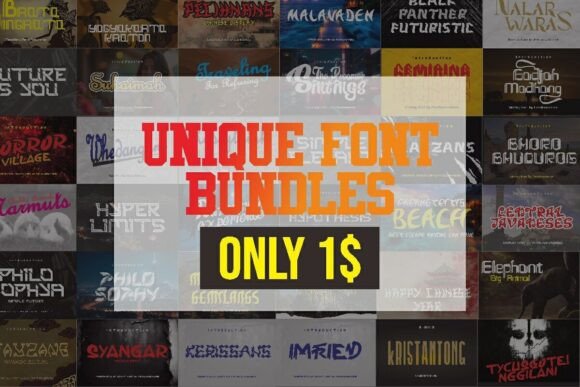
Unique Font Bundle
์˜ฌ๋ฐ”๋ฅธ ๋””์ž์ธ ์š”์†Œ๋ฅผ ์ฐพ๋Š” ๊ฒƒ์€ ์–ด๋ ค์šธ ์ˆ˜ ์žˆ์ง€๋งŒ Unique Font Bundle๋Š” ์ž‘์—…์„ ์ฆ‰์‹œ ํ–ฅ์ƒ์‹œํ‚ค๋Š” ๋›ฐ์–ด๋‚œ ์ปฌ๋ ‰์…˜์„ ์ œ๊ณตํ•ฉ๋‹ˆ๋‹ค.
์ •๋ฐ€ํ•˜๊ฒŒ ์ œ์ž‘๋œ Unique Font Bundle๋Š” ๊น”๋”ํ•œ ๋ฒกํ„ฐ, ๋ถ€๋“œ๋Ÿฌ์šด ํƒ€์ดํฌ๊ทธ๋ž˜ํ”ผ ๋ฐ ์•ˆ์‹ฌํ•  ์ˆ˜ ์žˆ๋Š” ์ƒ์—…์šฉ ๋ผ์ด์„ ์Šค๋ฅผ ์ œ๊ณตํ•ฉ๋‹ˆ๋‹ค.
POD(์ฃผ๋ฌธํ˜• ์ธ์‡„) ์ œํ’ˆ, ๊ฒฐํ˜ผ์‹ ์ดˆ๋Œ€์žฅ ๋˜๋Š” ์†Œ์…œ ๋ฏธ๋””์–ด ๊ทธ๋ž˜ํ”ฝ์„ ๋งŒ๋“ค ๋•Œ Unique Font Bundle๋Š” ์ด์ƒ์ ์ธ ์„ ํƒ์ž…๋‹ˆ๋‹ค.